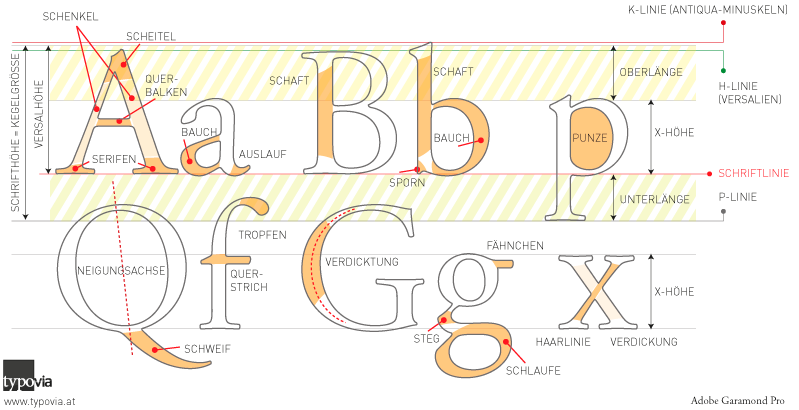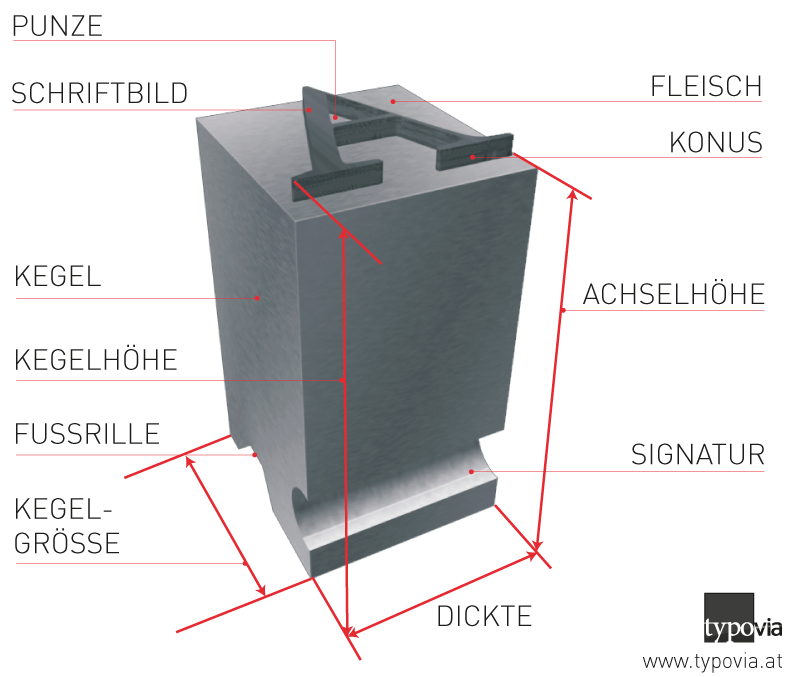
Das Zeichen (von althochdeutsch ‚zeihhan’, ‚zeihen’ = hinweisen) ist die abstrakte Idee eines Buchstabens, die Glyphe ist deren konkrete grafische Darstellung.
Die Fachbegriffe der Typografie stammen teilweise aus der Zeit des Bleisatzes und beschreiben die Komponenten des Buchstabens.
Hier wird ein Kegel, d. h. der Metallkörper, auf dem die Glyphe bzw. die Letter gegossen worden ist, herangezogen.
Seitenverkehrt gedruckt erhalten auch die abgedruckten Elemente der Letter eigene Bezeichnungen. Die Abbildungen stellen diese Komponenten anschaulich dar.